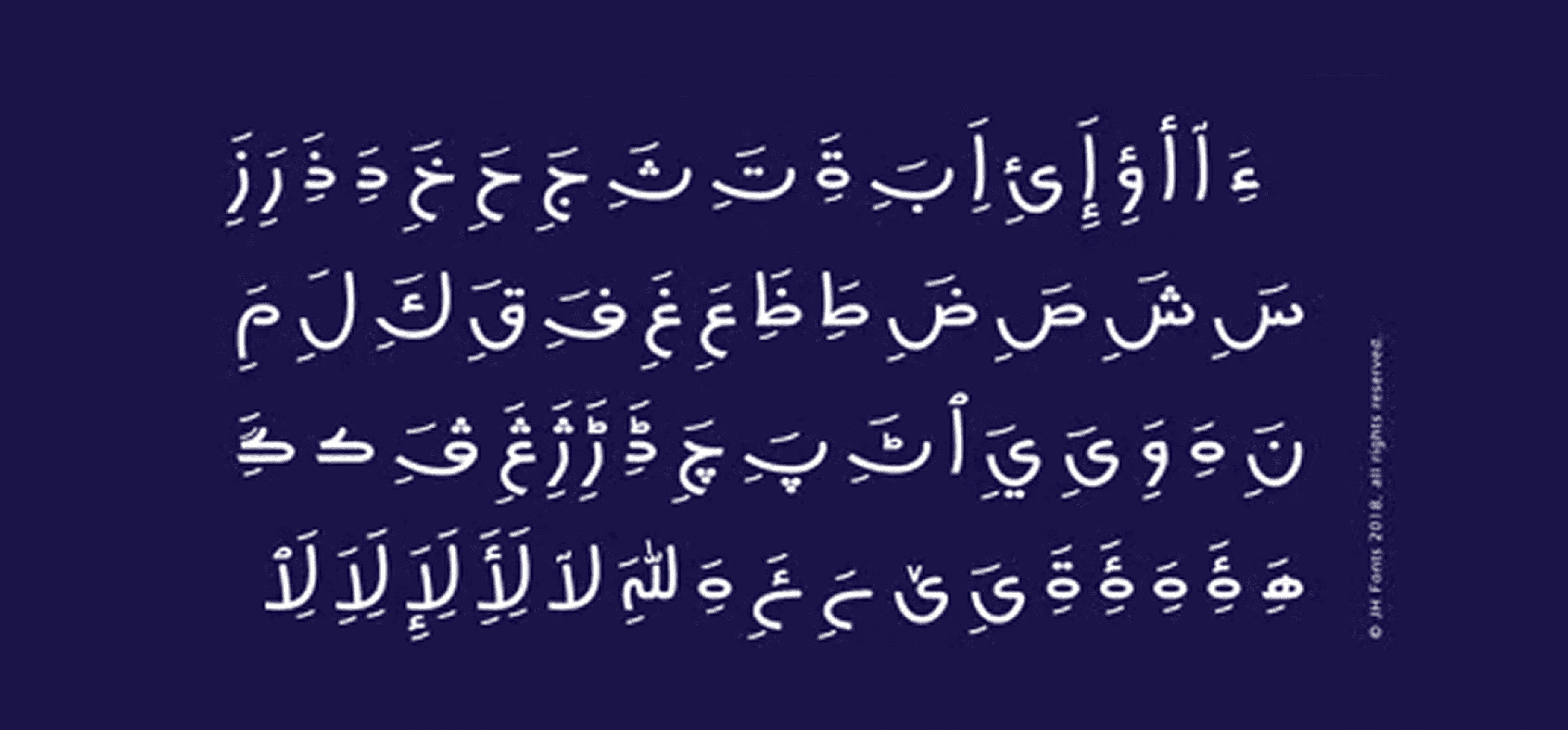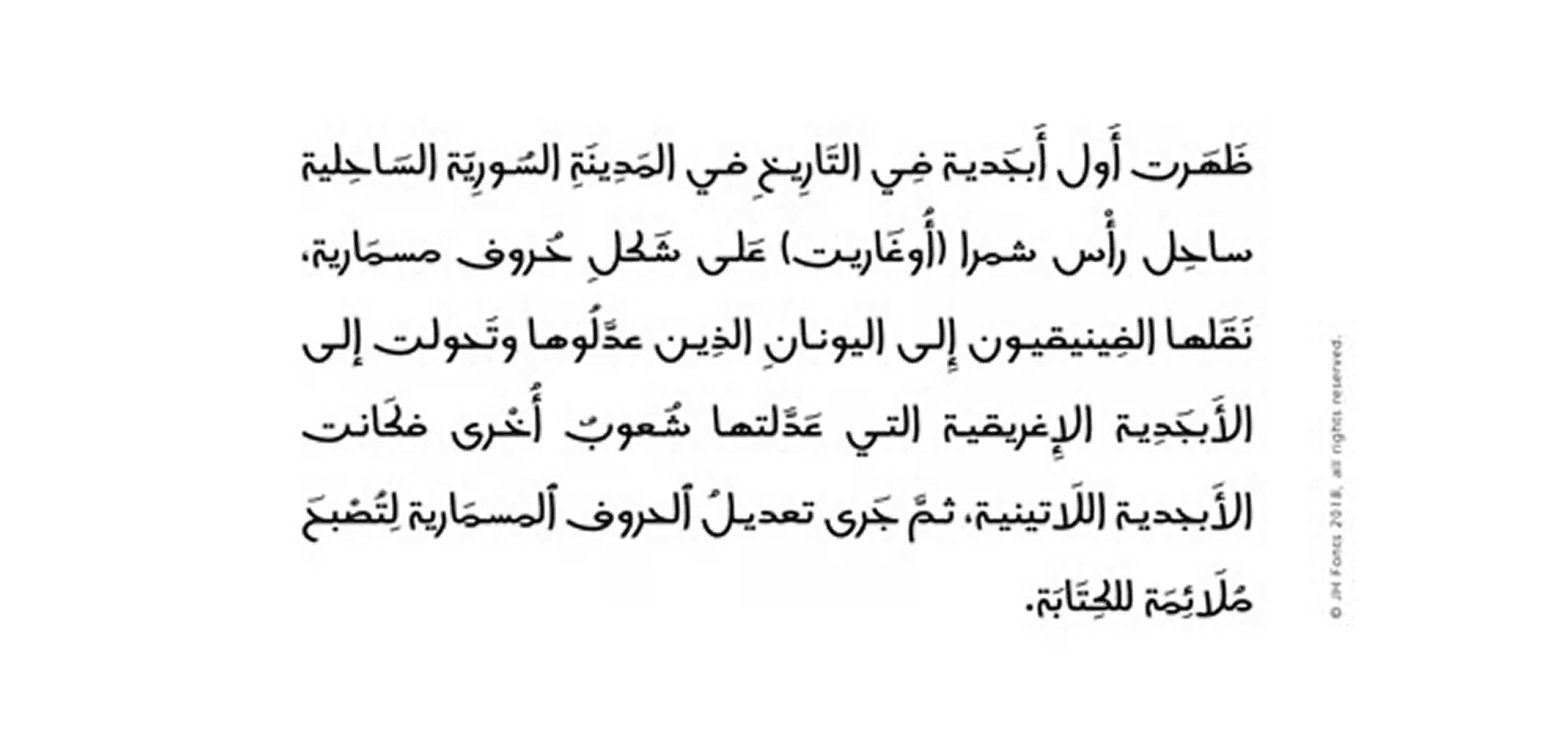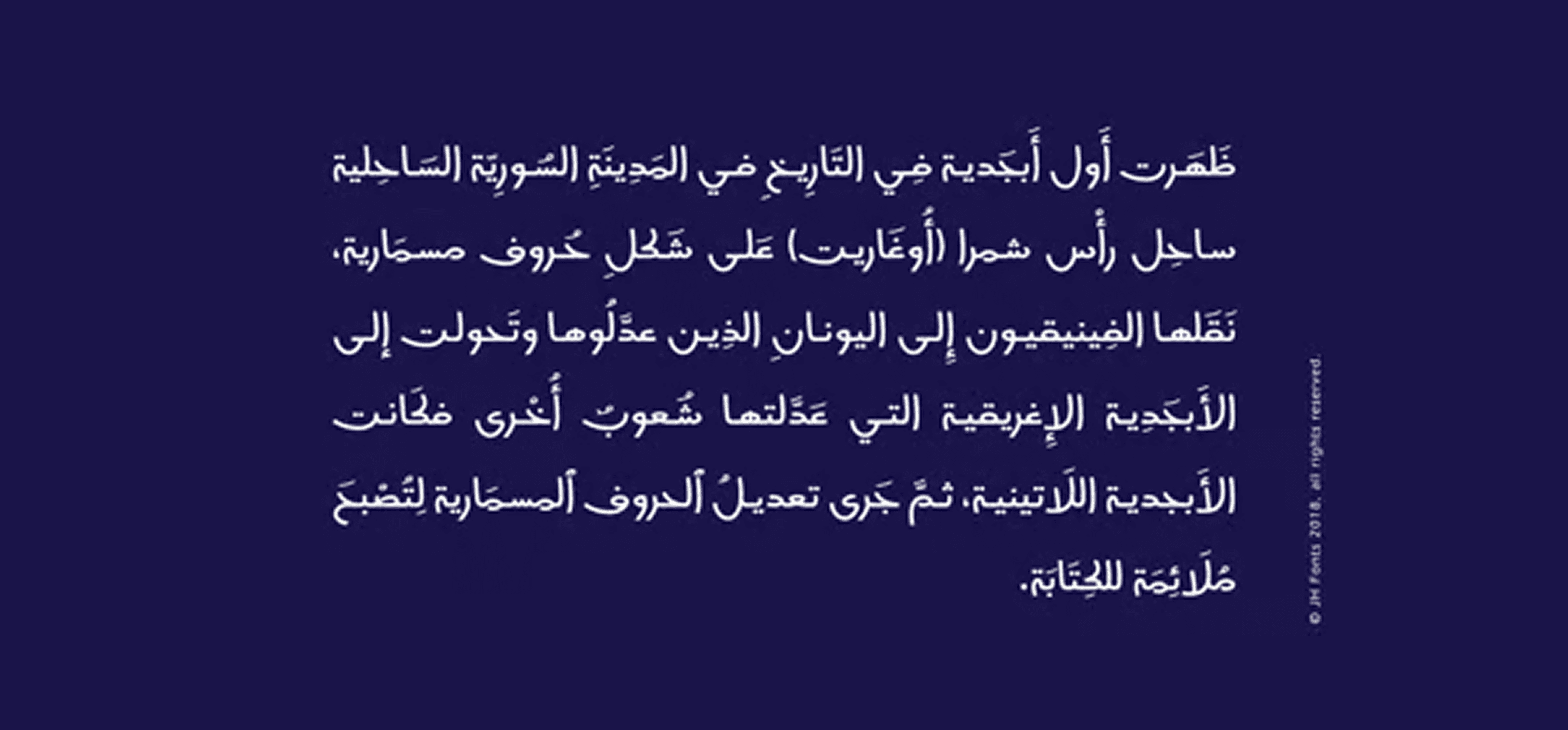
خط JH Mars هو خط ذو طابع عصري، تم تصميمه بالاعتماد على خطوط كوفية، مغاربية، وديوانية قديمة. وهو مثالي لاستخدامه في الهوية المؤسسية، العناوين، العلامات التجارية، واللافتات.